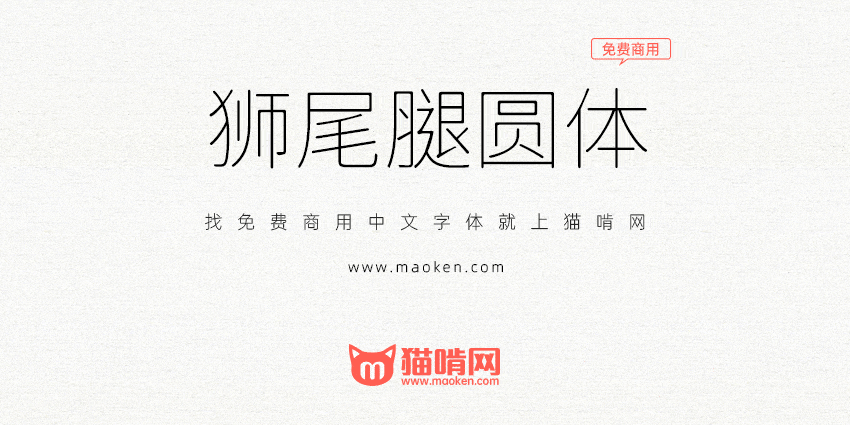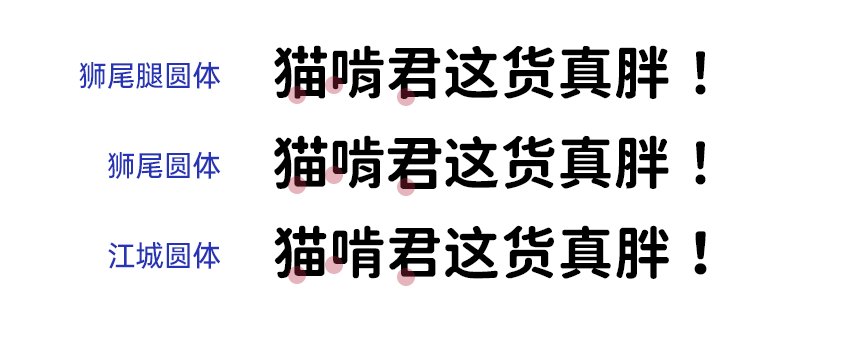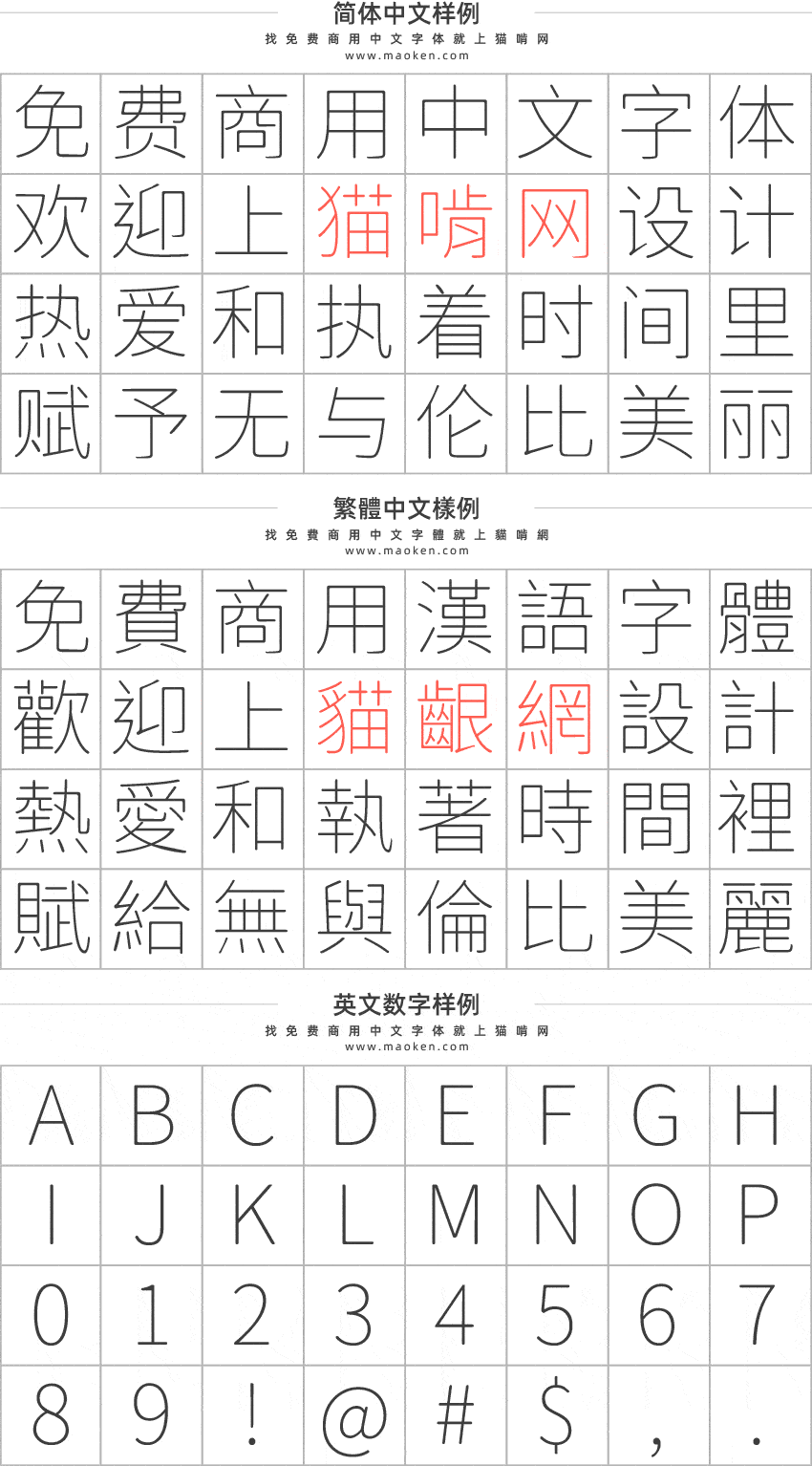
狮尾腿圆体是台湾的大神Max又一款基于思源黑体变圆改造,和狮尾圆体的差别在有长腿,更加简明现代化的字体。支持简体中文、繁体中文、韩文与日文;欢迎大家自由应用、自由优化、自由改作!
狮尾腿圆体和狮尾圆体差别在有没有拔脚。狮尾圆体是“有拔脚”的,字会较圆,但是会造成有些字因直接去掉腿后左右不平衡、左右不对衬的“悬空”问题。使用“腿”系列就比较不会有失衡的问题,但是看上去还是会有黑体的感觉。
狮尾腿圆体是基于思源黑体改造而成,所以无论是简体还是繁体基本上都不缺字,并且拥有7个字重。
- 调整套用效果的细节。可以比较新旧版的文字:人姵嚠。
- 调整套用转角的细节设定,还有调整贝兹曲线的判断。
你好!想问下这个字体的标点符号为什么全部在中间位置的?
那是台標字形的!
那这个字体版本就是对应大陆版的资源圆体了,由思源黑体架构改造成有脚的圆体
狮尾好些字体有个小bug,部分字重里“拔”字显示风格错误变成普通宋体,你自己测试一下看看,我也是无意中发现的。这里只说简体版的
是没有“拔”这个字,不知道MAX怎么把这个字弄掉了
CJK TC 沒有缺,CJK SC 缺,下一版會修正。